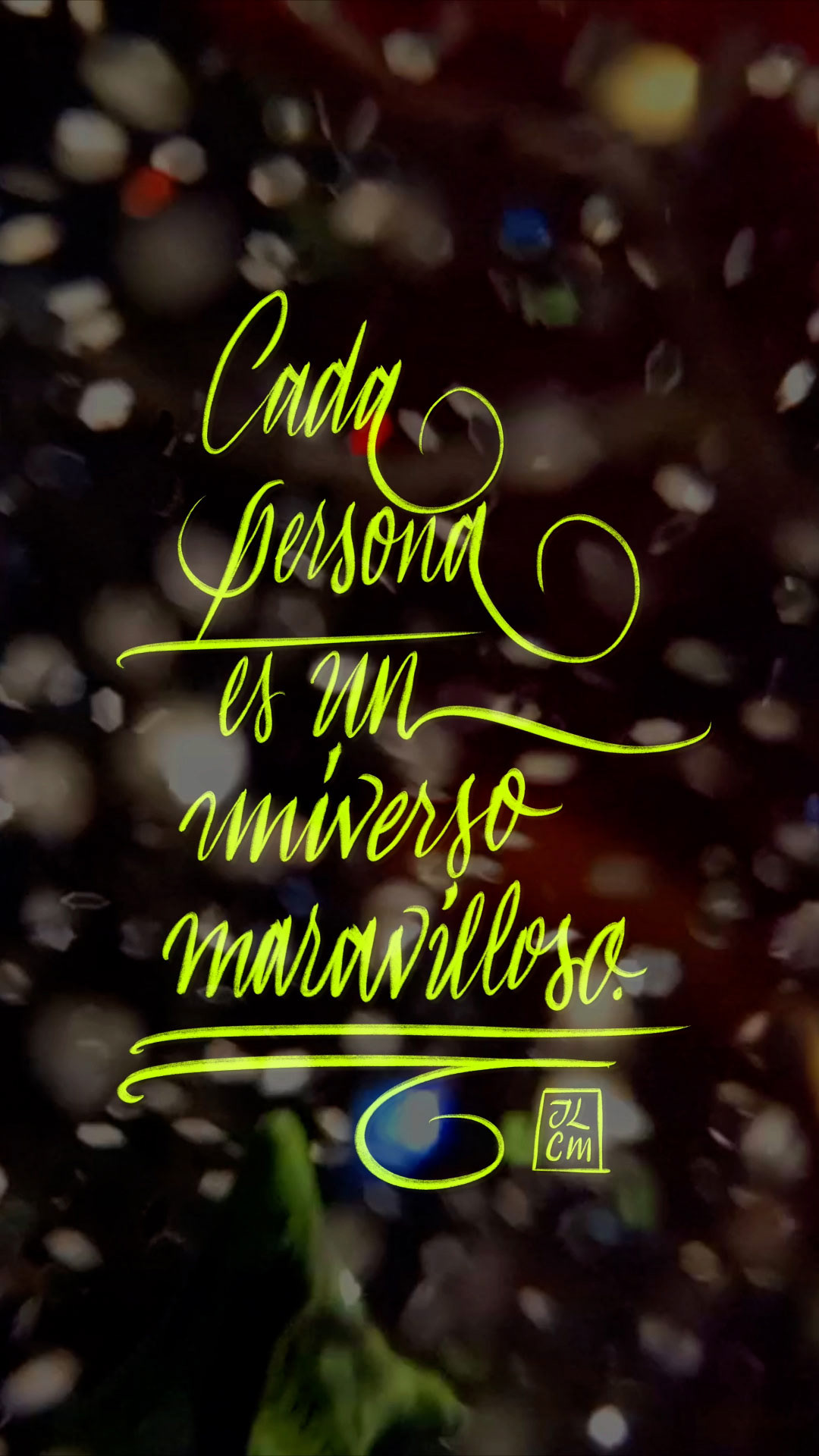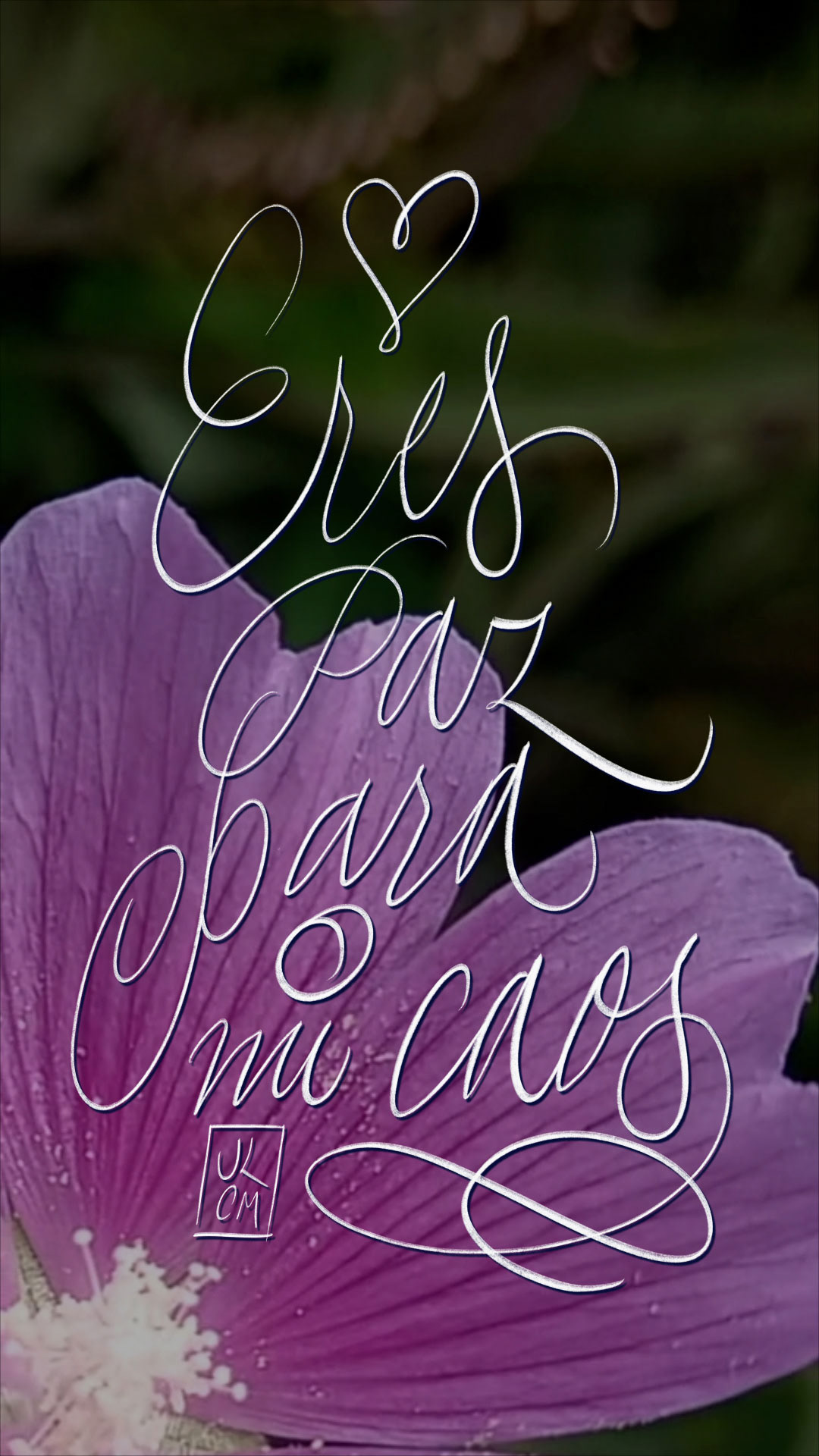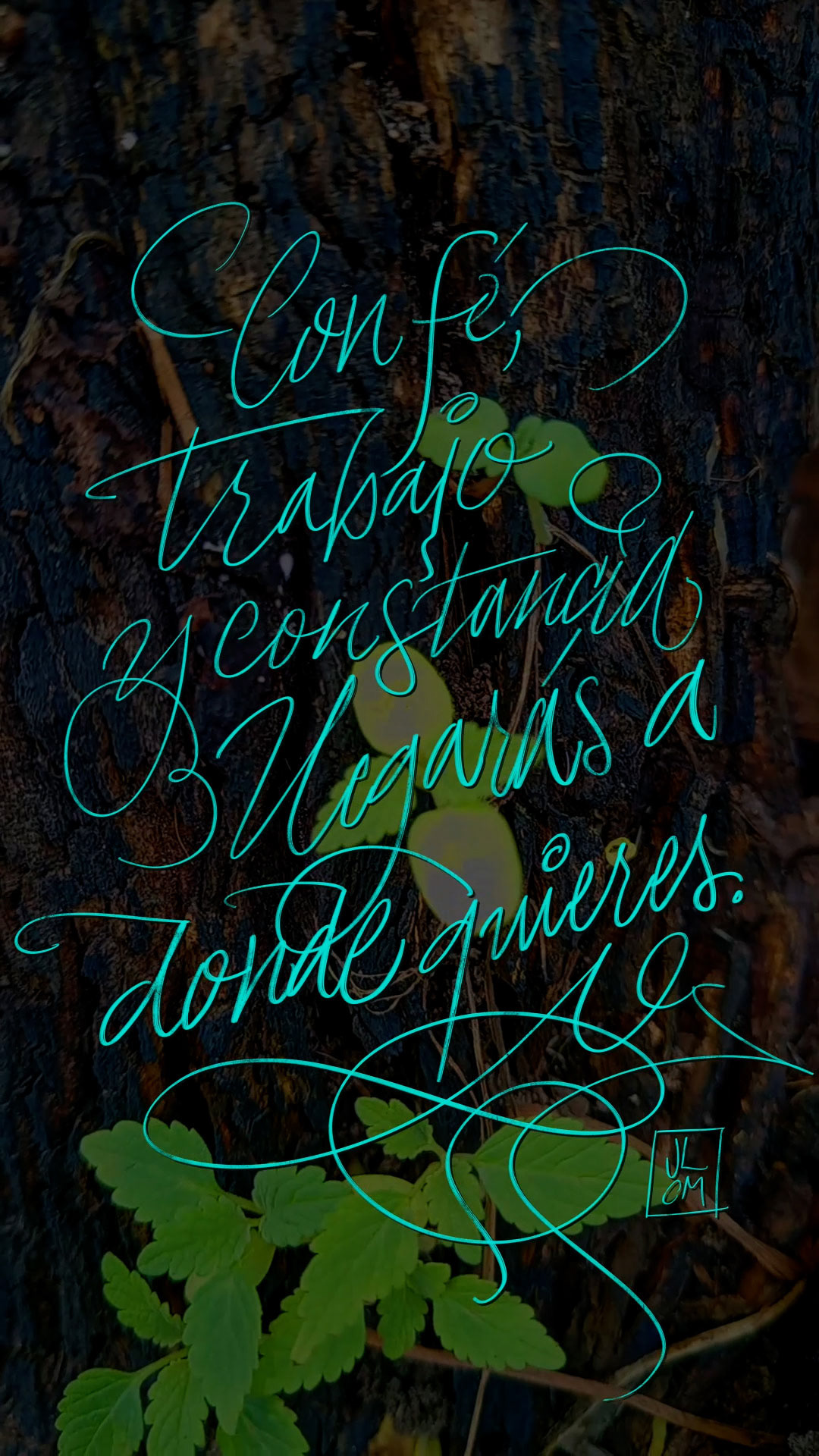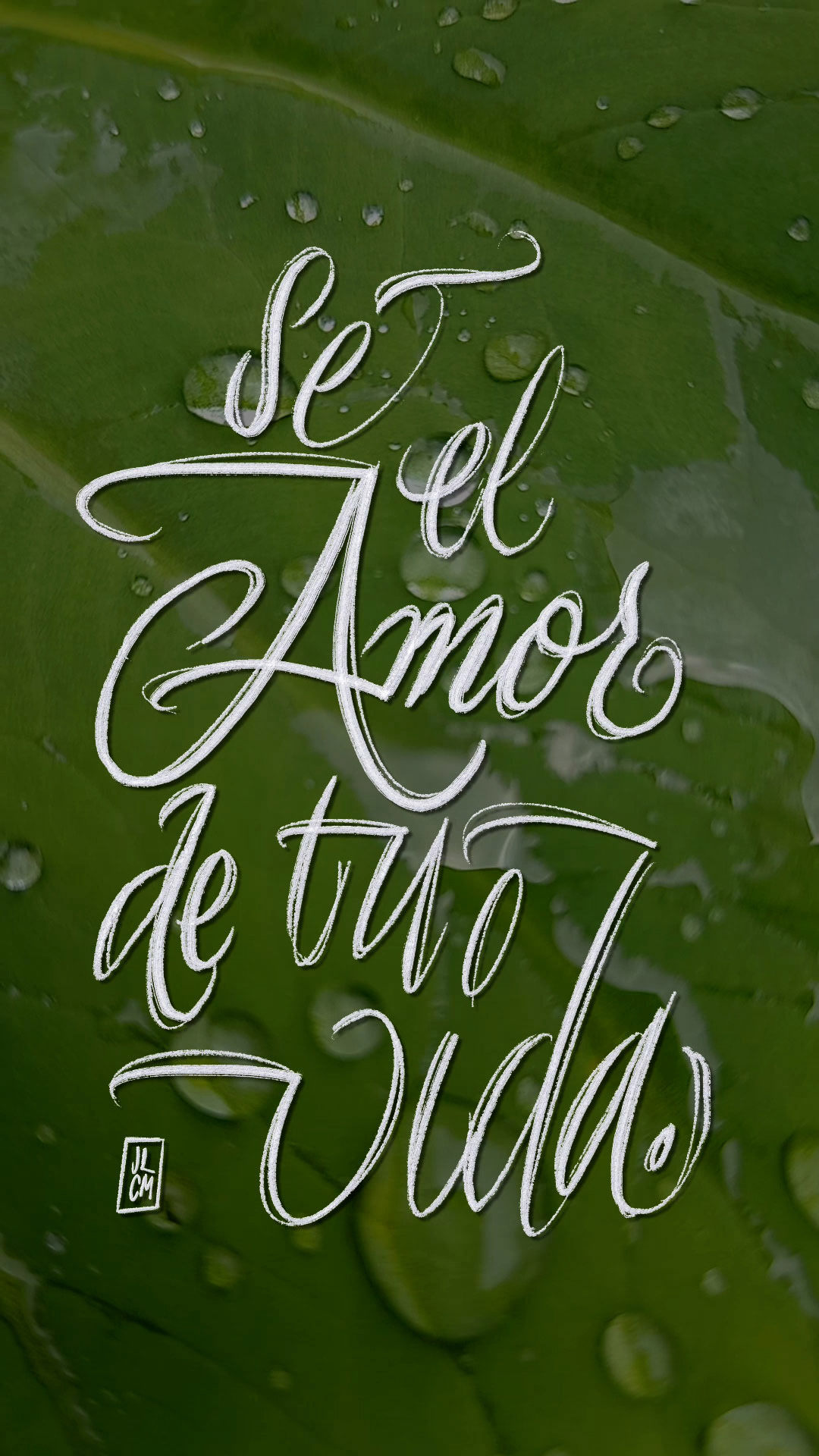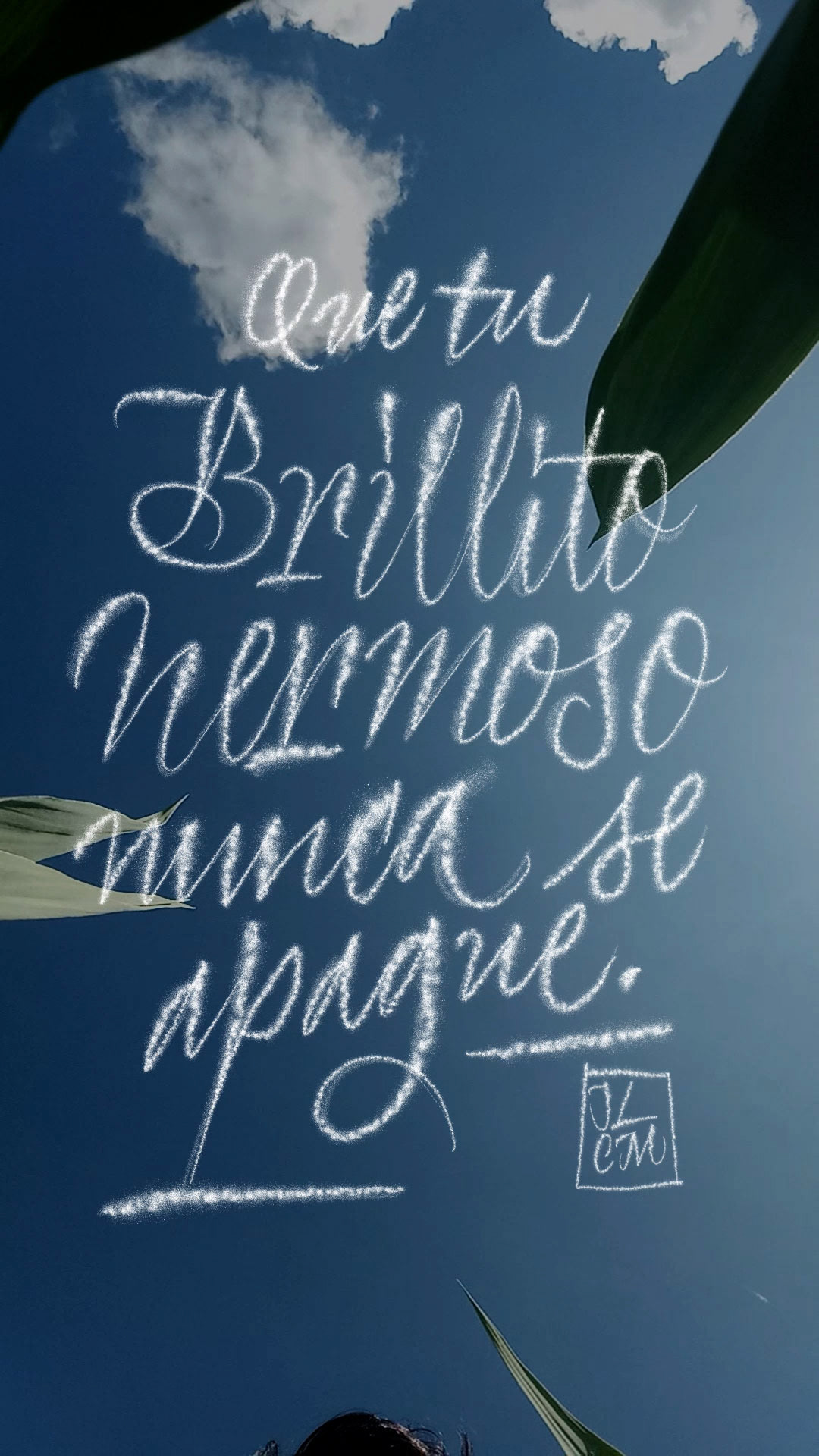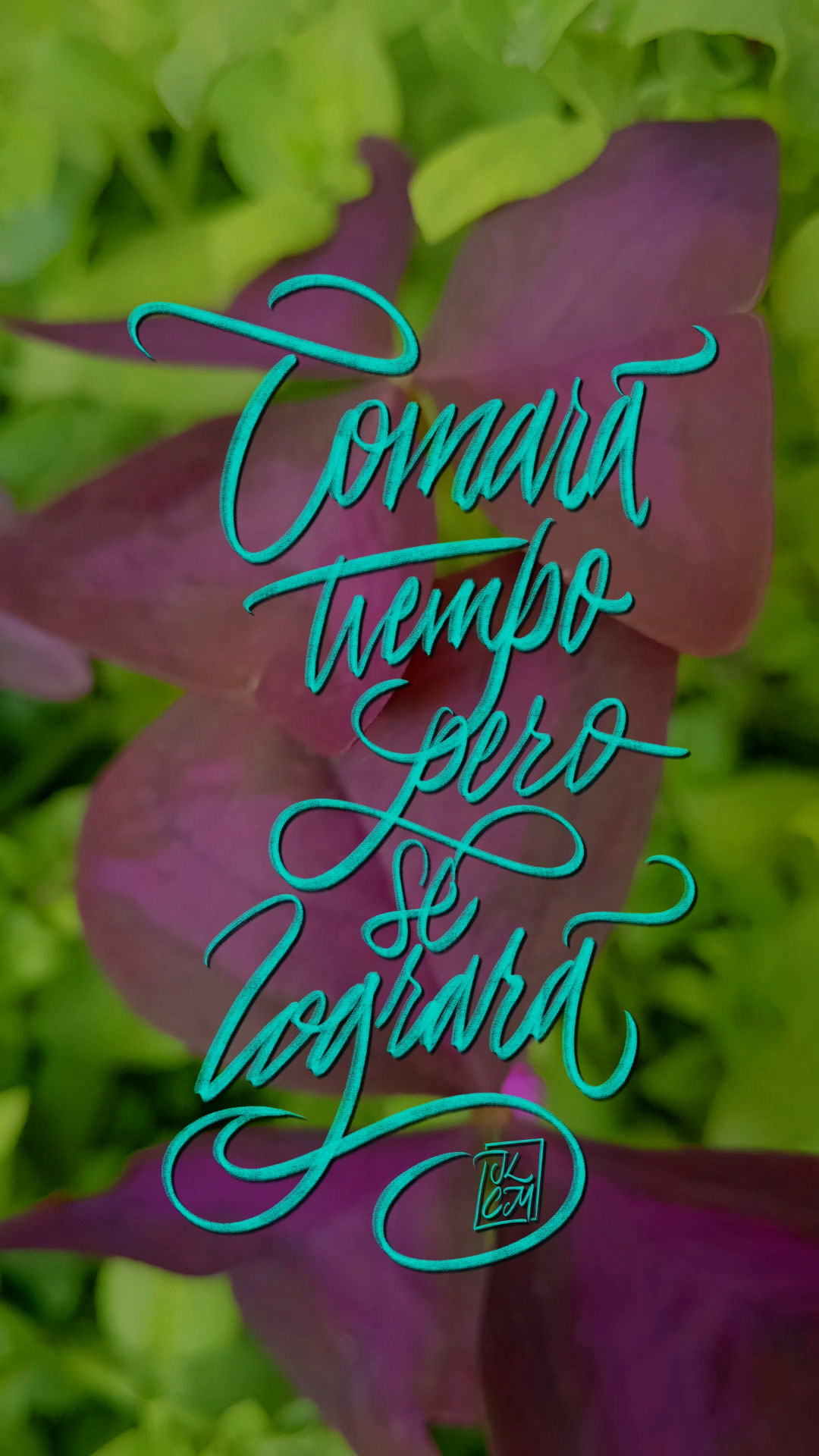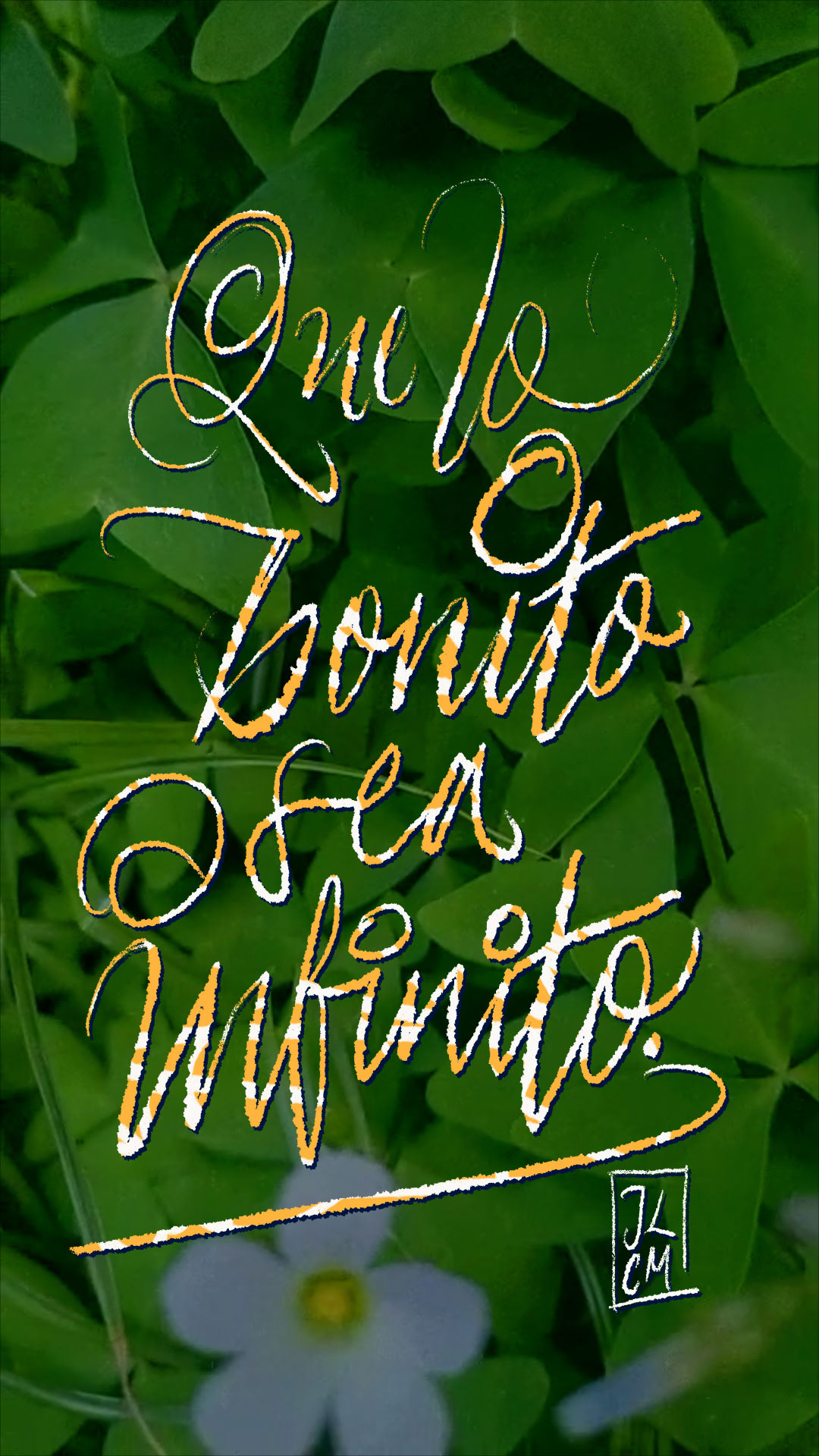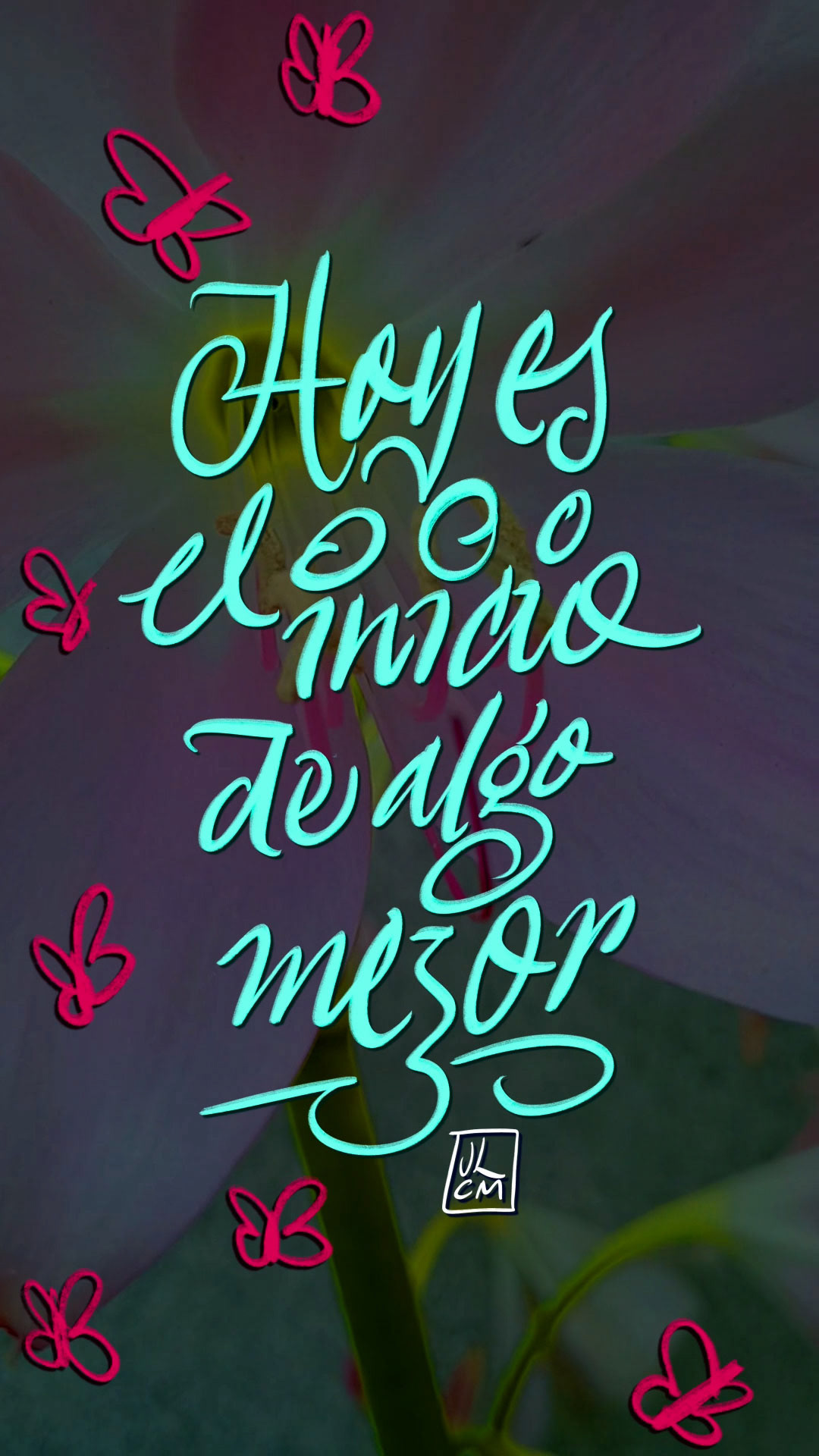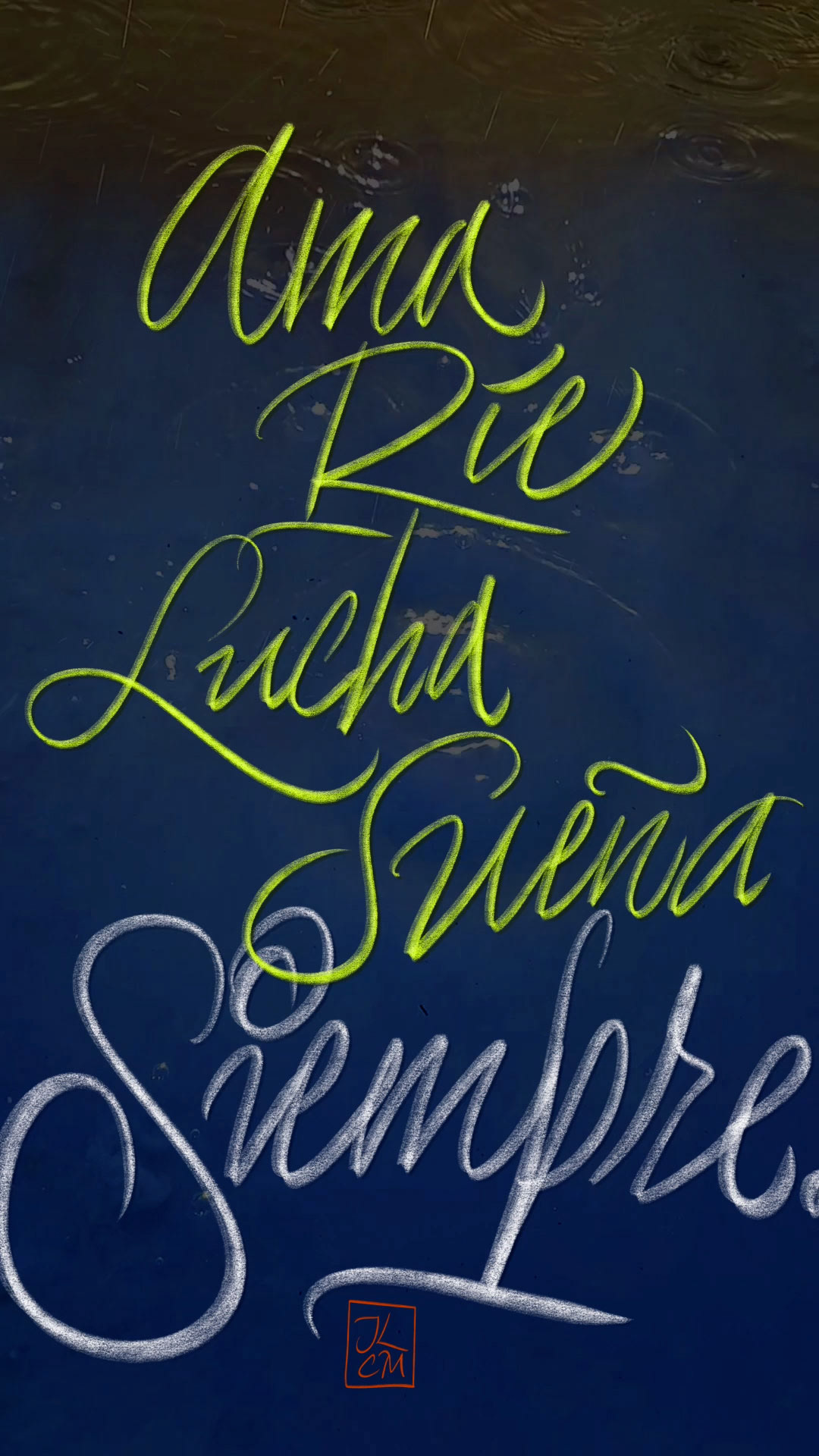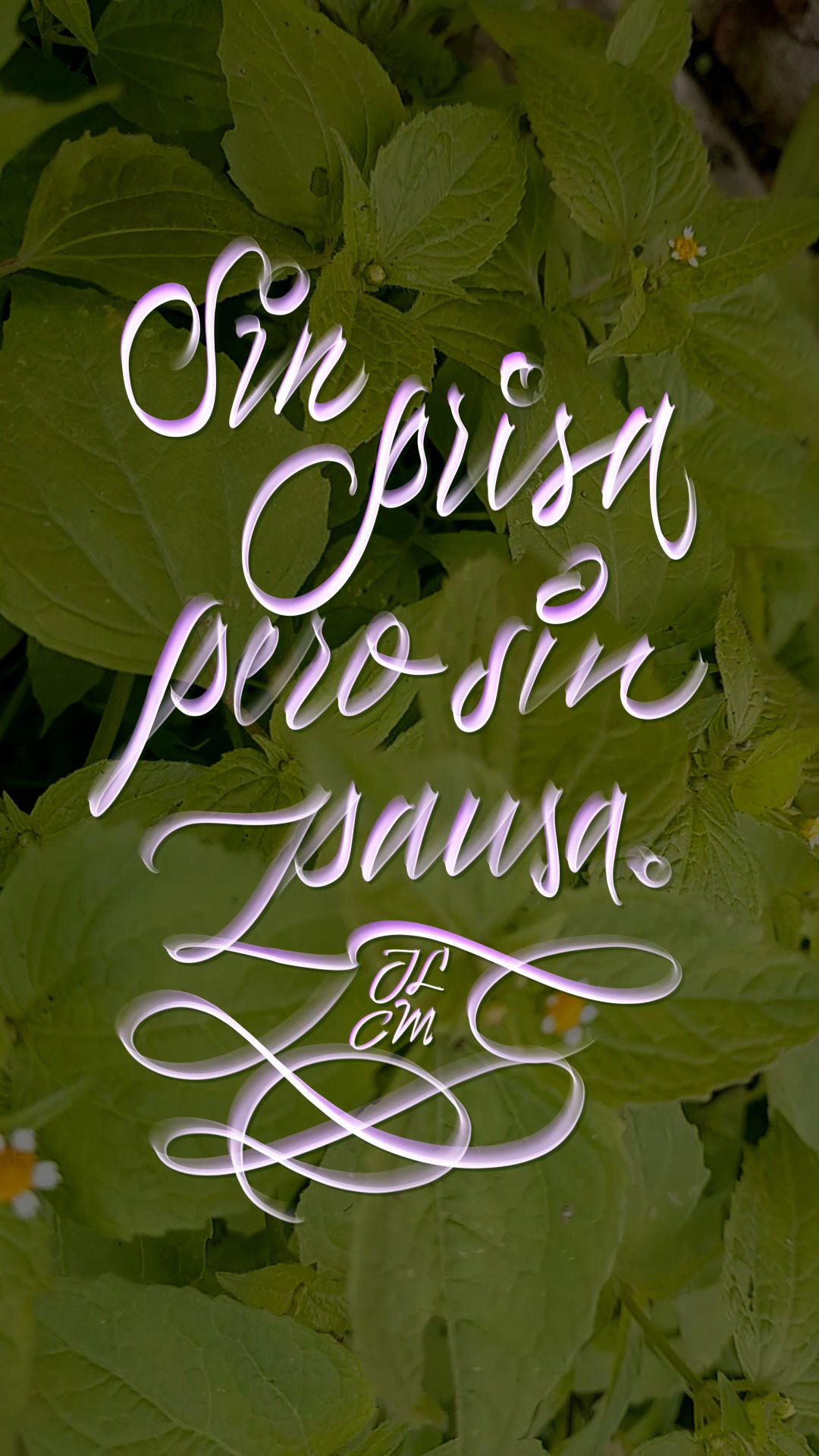
EL SOL CAMINA CONMIGO 3
Tercera parte de "El Sol Camina Conmigo", el proyecto que consiste en el diseño de una serie de postales digitales e historias para redes sociales con mantras sencillos pero positivos sobre el amor y la plenitud de vivir. En esta colección, se combinaron composiciones en lettering gestual con herramientas de Procreate, así como elementos de video grabados por mí.
Ésta tercera colección tiene 22 piezas creadas en 2025 para redes sociales, principalmente Instagram y Facebook.